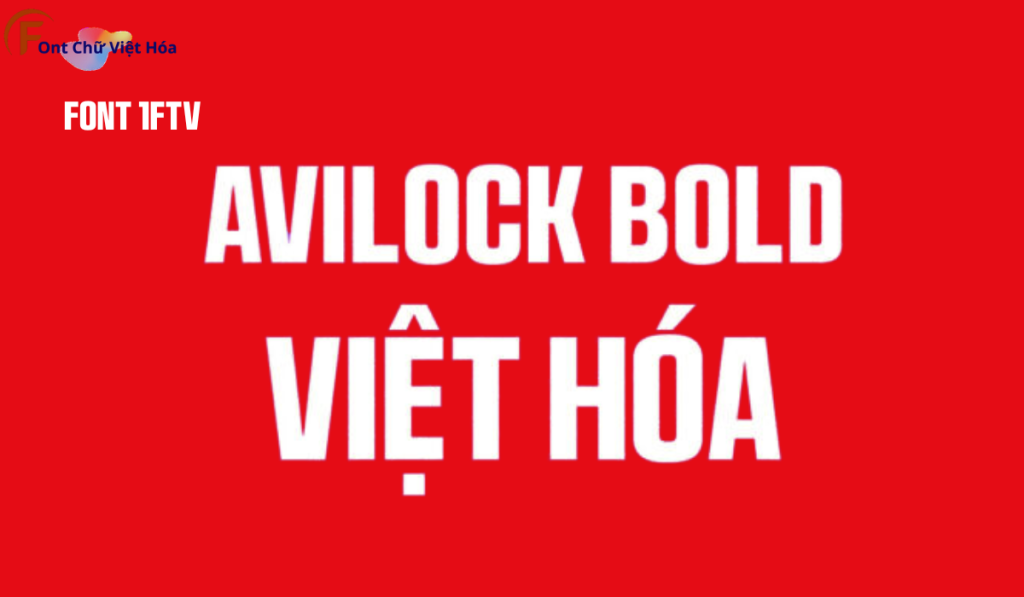
Font 1FTV Avilock Bold Việt hóa
Tác giả: 1FTV
Bộ Font: 1FTV
Độ dày: Bold
Font 1FTV Avilock Bold là một font thuộc bộ Font 1FTV, mang phong cách thiết kế đậm và mạnh mẽ. Với các đường nét không chân, font này tạo cảm giác chắc chắn và hiện đại, giúp nhấn mạnh các nội dung quan trọng trong thiết kế. 1FTV Avilock Bold đặc biệt phù hợp cho tiêu đề, banner, và các dự án yêu cầu sự nổi bật. Font này cũng hỗ trợ tiếng Việt đầy đủ, giúp các nhà thiết kế dễ dàng sử dụng trong các dự án đa ngôn ngữ mà không làm mất đi sự thẩm mỹ và chuyên nghiệp.